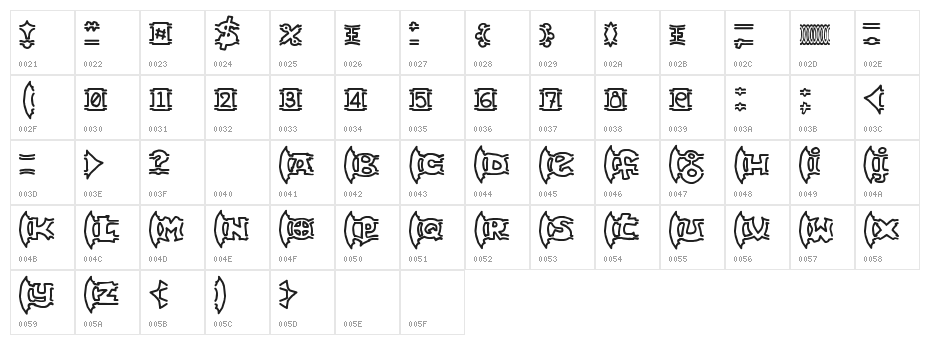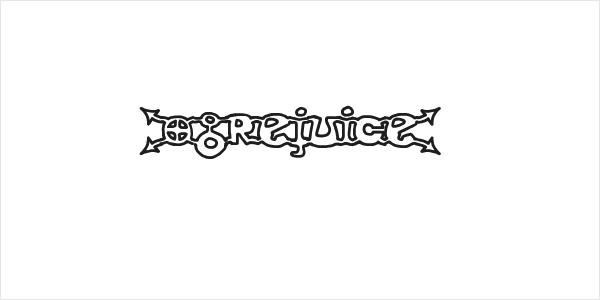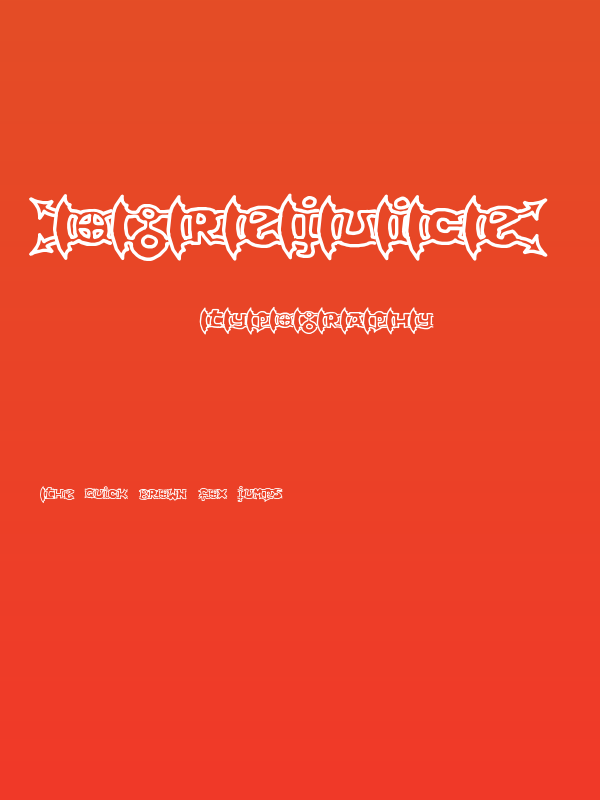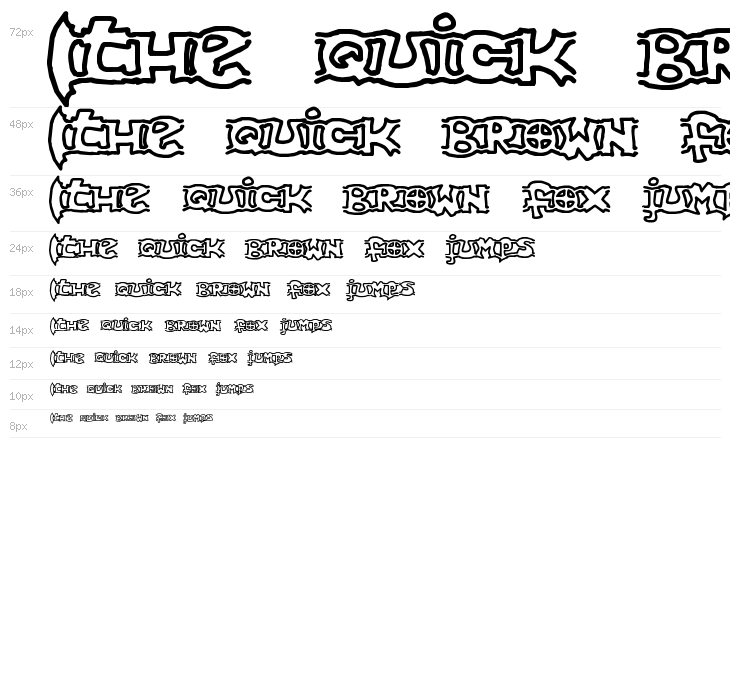
{ogrejuice} Font
| Progetti proposti | Ideal for fantasy-themed posters, video game titles, book covers, and any project requiring a dramatic and eye-catching typeface. |